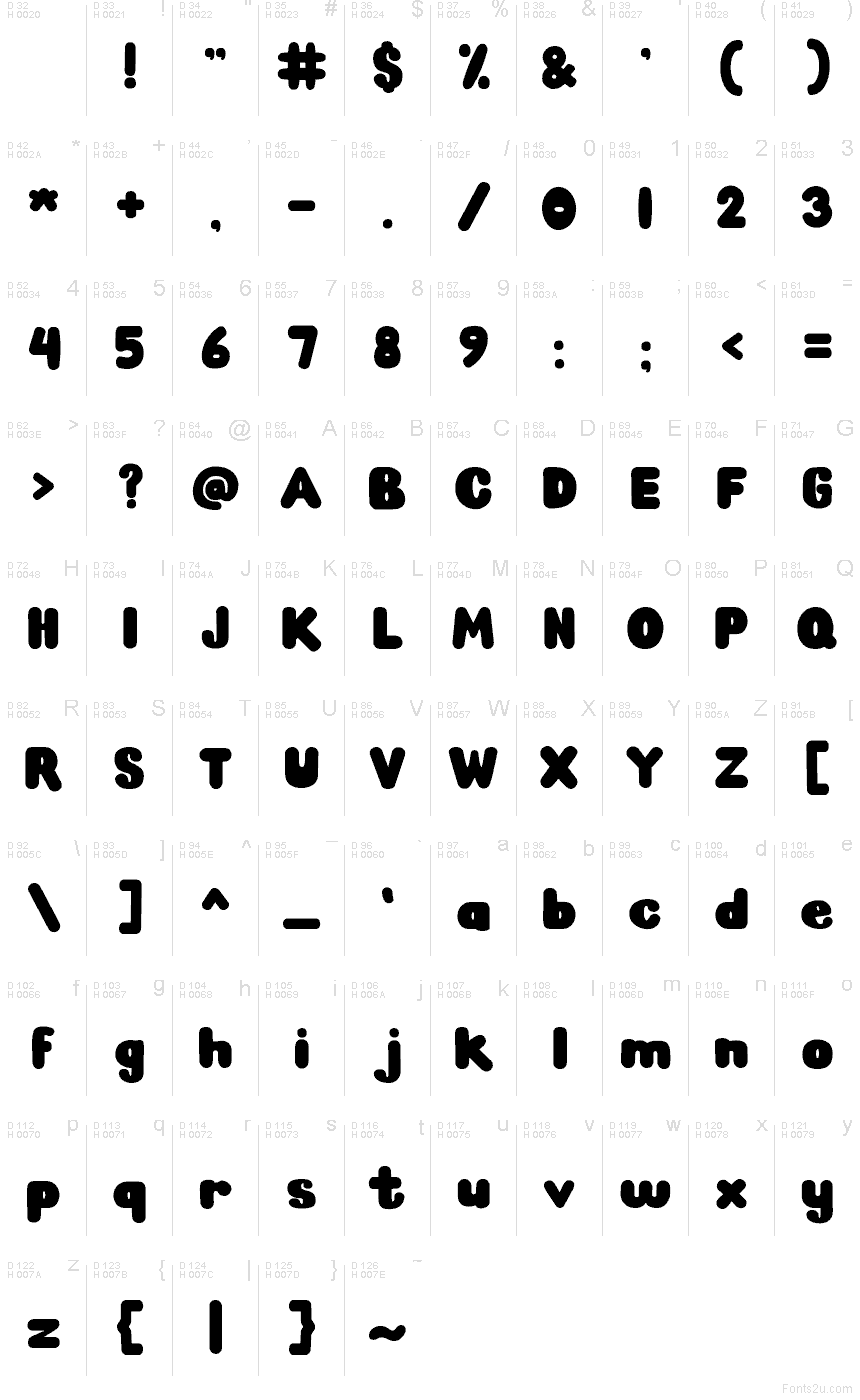
Hypero de Pinisiart es una tipografía display gratuita de estilo cartoon, con letras grandes y abultadas y un aire retro pop alegre. Sus formas son densas y redondeadas, con curvas suaves, uniones precisas y algunos recortes originales que mantienen la tipografía dinámica en lugar de plana.
Es ideal para titulares de pósteres, envases infantiles, pegatinas, miniaturas de YouTube y branding lúdico donde se busquen palabras cortas con un impacto cercano. Al ser una fuente gratuita, Hypero funciona de maravilla para títulos y portadas, ya que su silueta gruesa y sus curvas exageradas dan a incluso las letras más sencillas una presencia divertida, casi como si estuvieran hechas a mano.